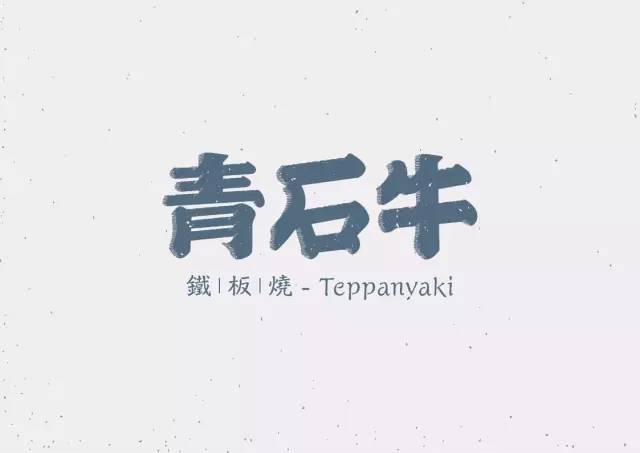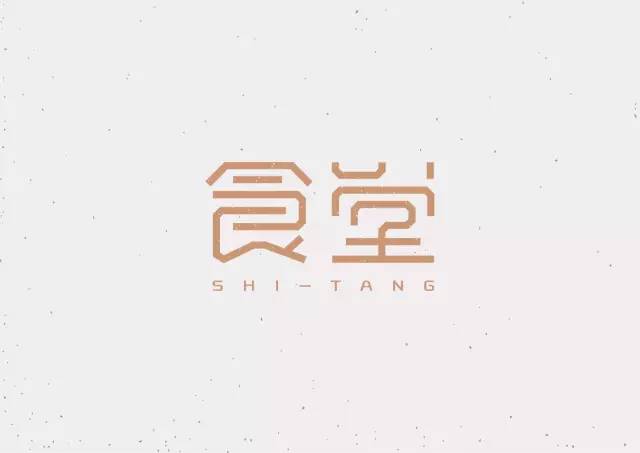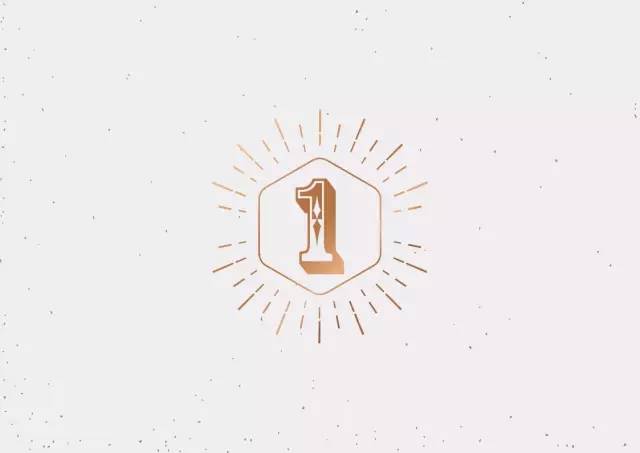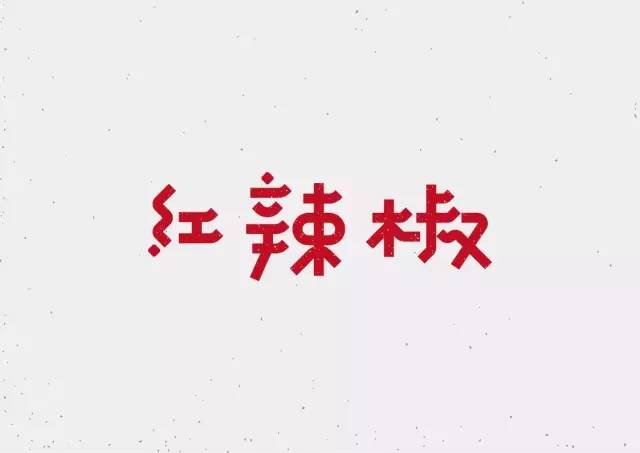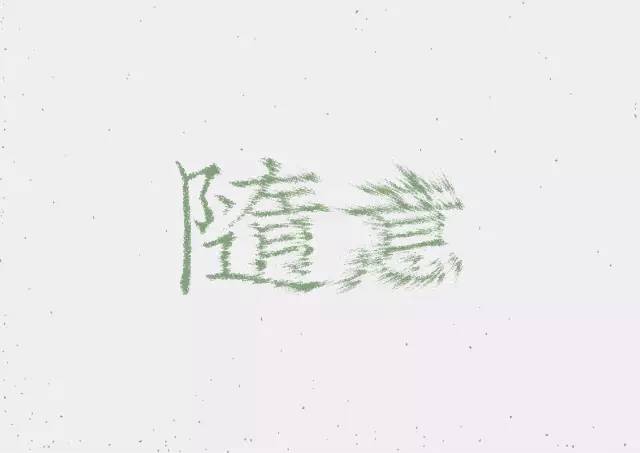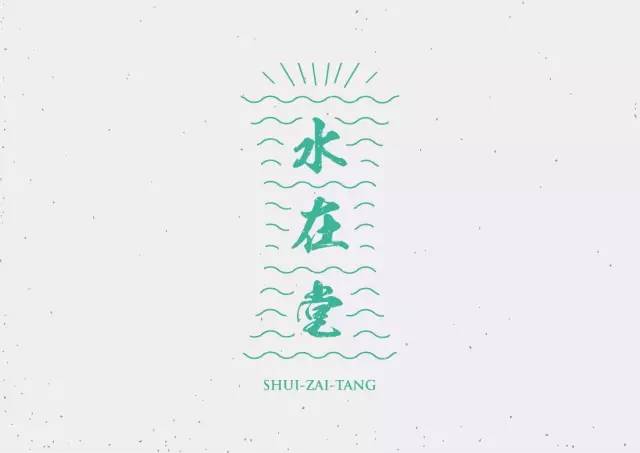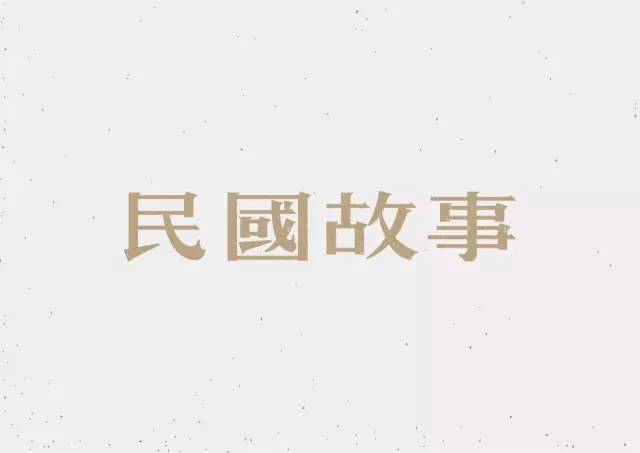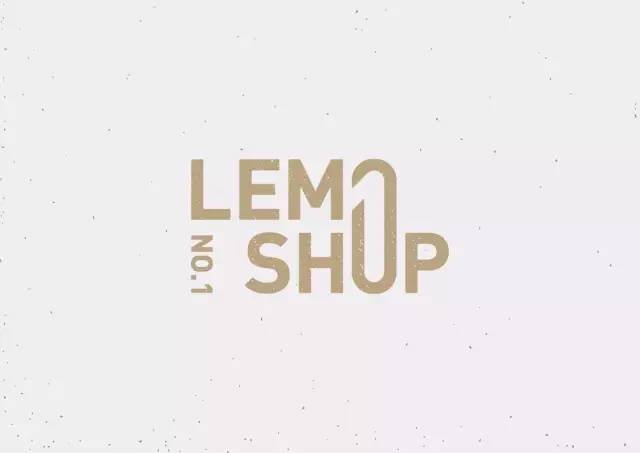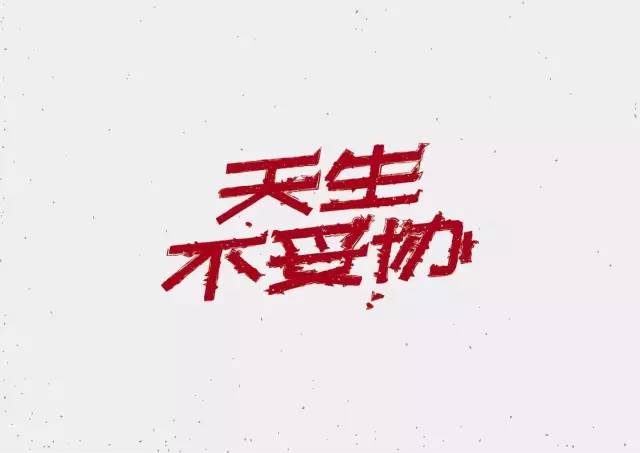
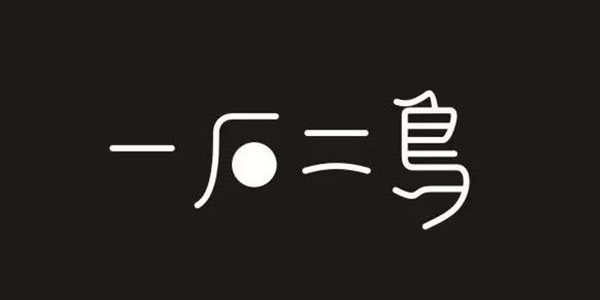
字体设计 | 每周设计案例欣赏
一些非商用的字体设计案例设计作品合集作品,大家收藏作为灵感来源吧!
梦境漫游
随意
上海
萬源
拾里长亭
不战而败
自然风
梦里花
夏朵西
这么近 那么远
海芋恋
梦
百年百日
而 饲 意 空··· ···太难认了,说实在的如果设计的字体会造成认知上的障碍,那么也是得不偿失啊!
生旦净末丑
一石二鸟
晚安
旅行的意义
倾心
素年锦时
蓝色空气
味百汇
紫云玄清
东京
御风